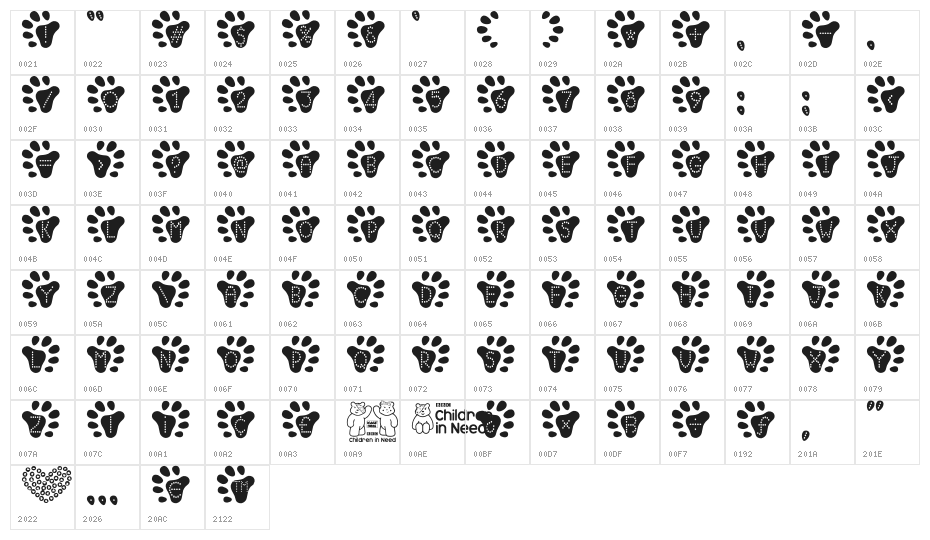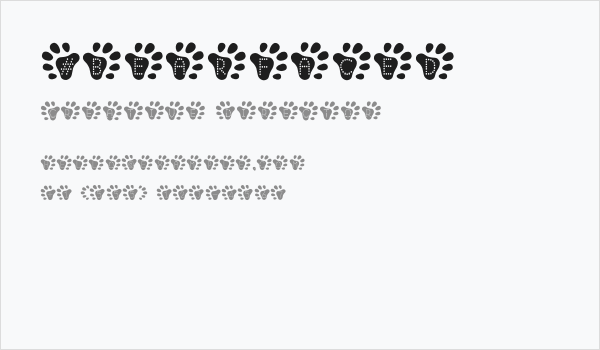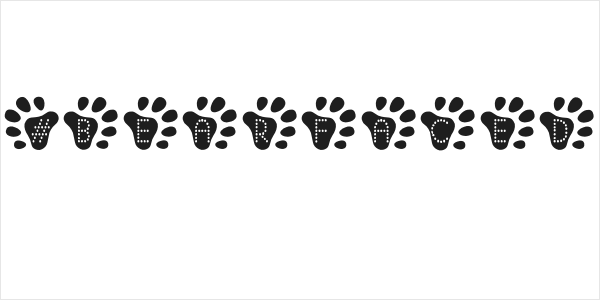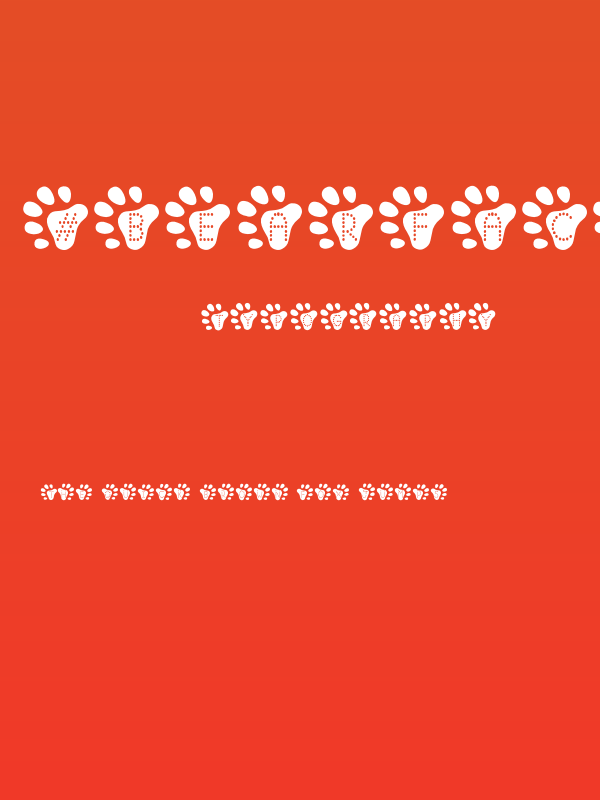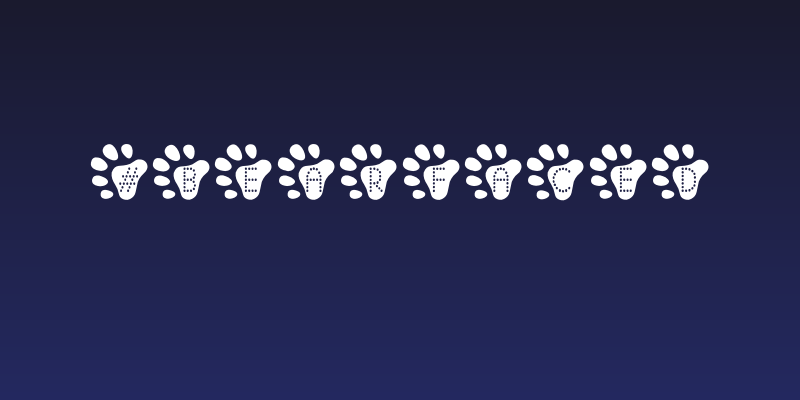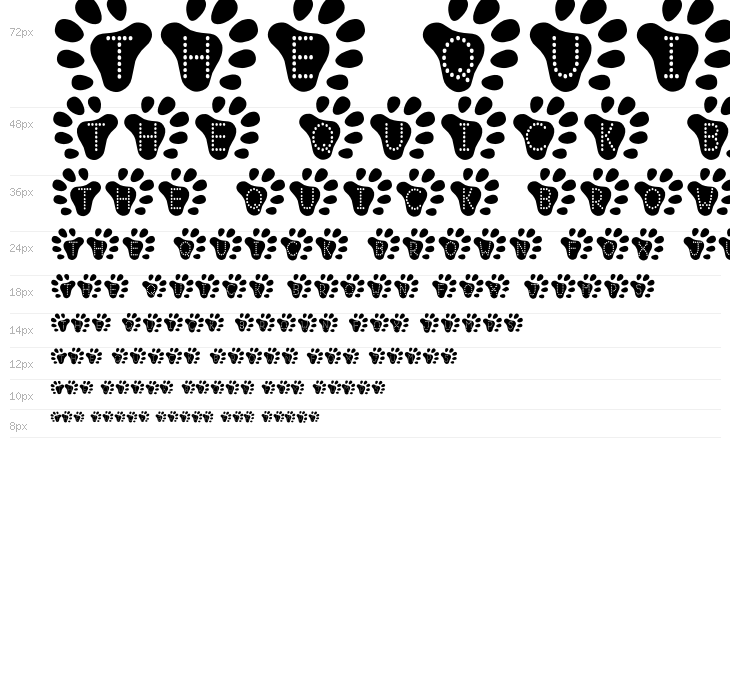
#bearfaced Font
✎ Dotted
BEARFACED MAIUSCOLE
BEARFACED MINUSCOLO
BEARFACED ALTRI CARATTERI
| Stile generale | Playful, Whimsical |
| Caso d'uso | Logos, Headlines, Decorative Text |
| Progetti proposti | Ideal for children's books, pet store branding, playful invitations, and educational materials. |